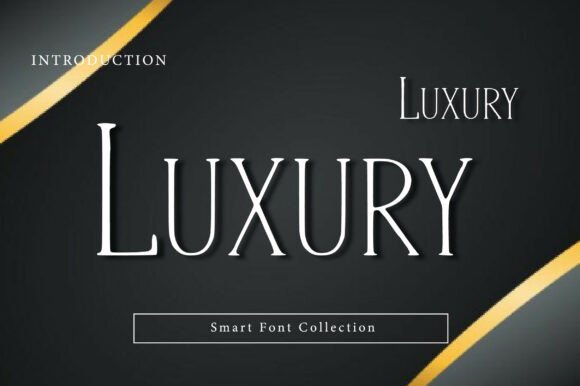
Luxury
Luxury — La typographie qui ravira
Luxe & Elegance : Pourquoi la typographie Luxury est le choix idéal
Dans le monde de la communication visuelle, chaque détail compte. C'est ici que la Luxury s'élève, offrant une solution perfecte pour créer des designs raffinés, raffinés et mémorables.
Qu'est-ce que la typographie Luxury ?
- Design élégant : Ses lignes épurées et ses proportions soigneusement étudiées confèrent une touche de sophistication.
- Polyvalence : Adapté à une multitude de projets, de la marque de luxe aux designs éditoriaux.
- Lisibilité optimale : Que vous utilisiez ce type sur une invitation de mariage, une boîte premium ou un magazine, la clarté est préservée.
Que vous soyez un designere, un brandinger ou un professionnel, la typographie Luxury est là pour vous. Son approche minimaliste allie modernité et prestige, tout en restant accessible.
Transformez vos idées en une expérience luxueuse avec Luxury. Idéal pour des projets où chaque mot compte. Découvrez comment cette typographie peut rehausser votre identité visuelle et votre savoir-faire.